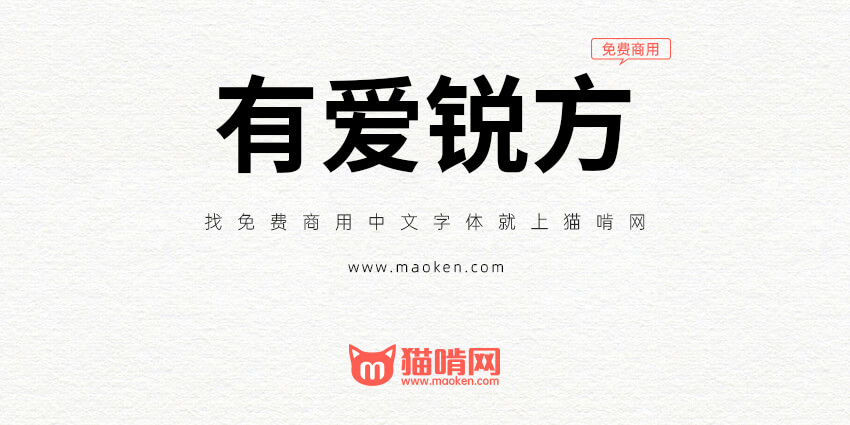
有爱锐方:《魔兽世界》字体包 微调文字边缘清晰锐利
字体作者:Cyano Hao (中国大陆) 字体字重:4个
字体名称:有爱锐方PS中字体名称:有爱锐方 CN
有爱锐方是《魔兽世界》和《魔兽世界:经典怀旧服》字体包,支持所有语言。有爱锐方通过字形微调技术,使文字边缘清晰锐利。 有爱锐方有5种字重和9种地区变体。
漂亮,英文和数字宽度再宽一点就完美了!